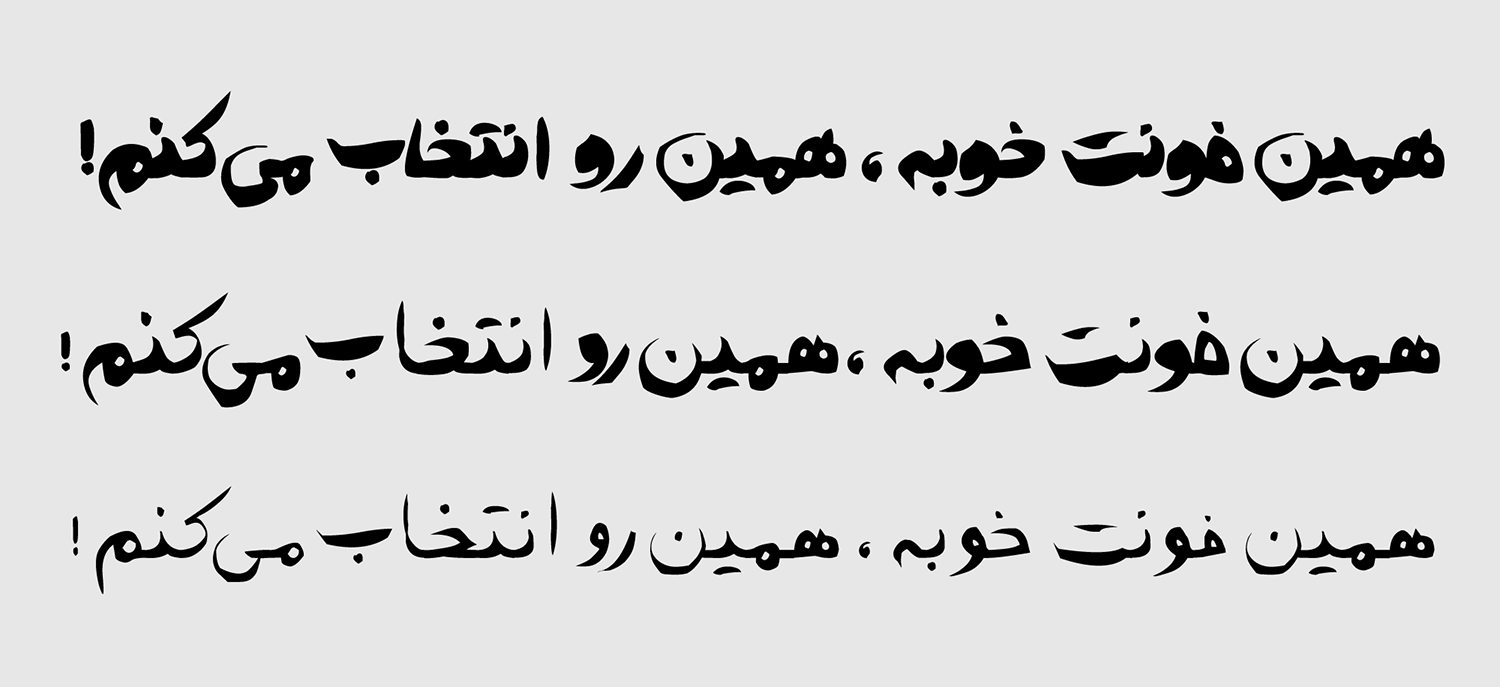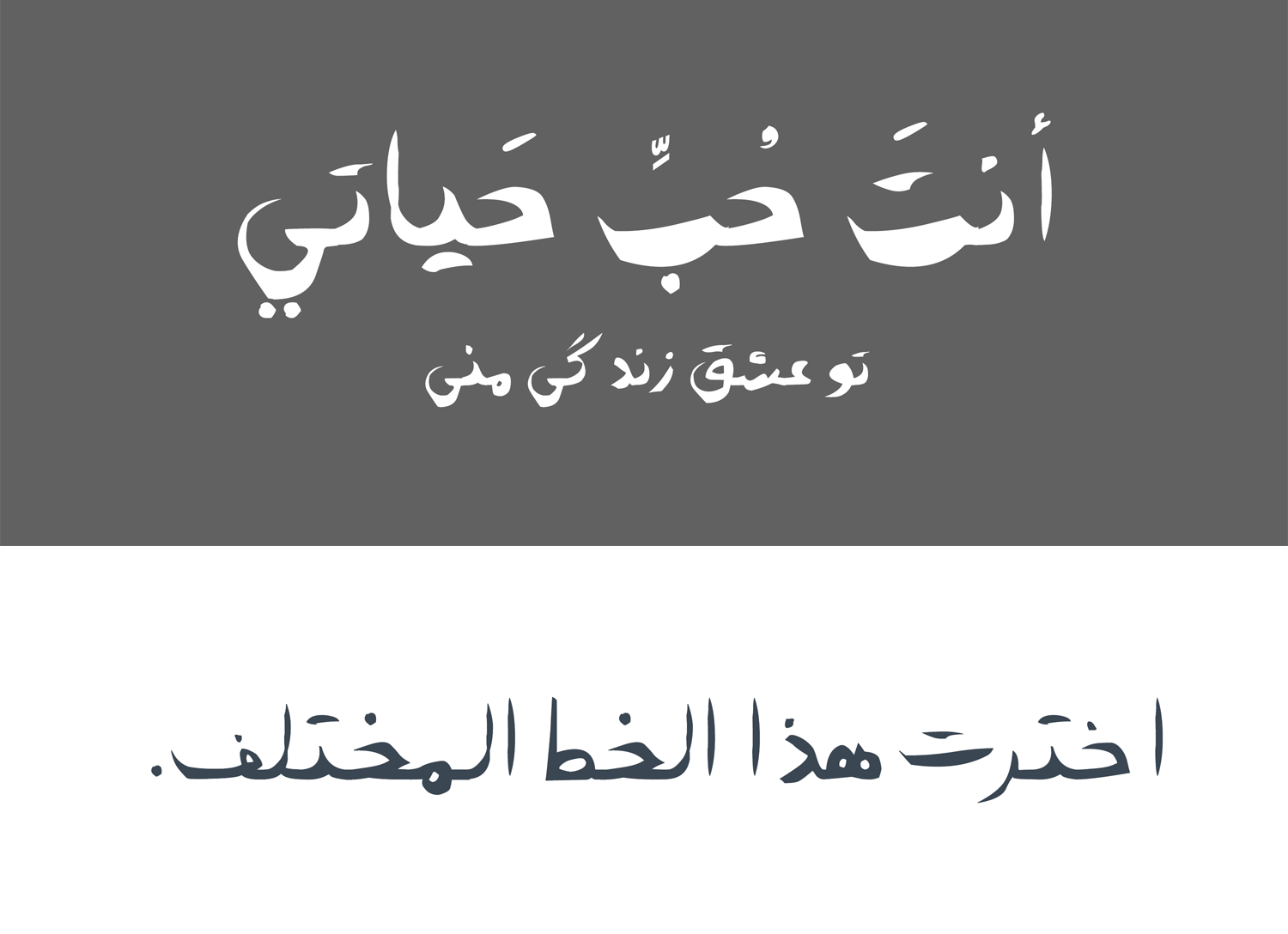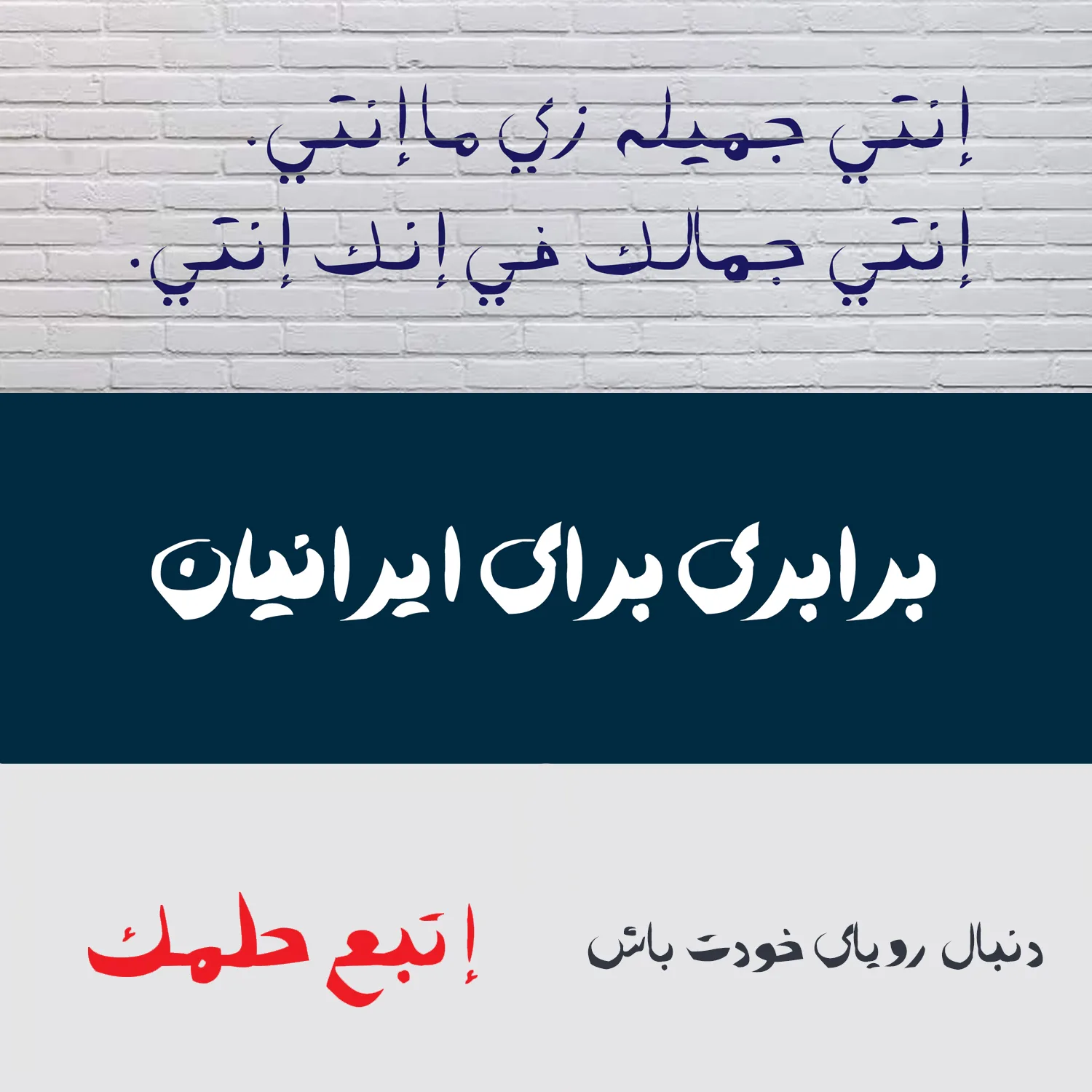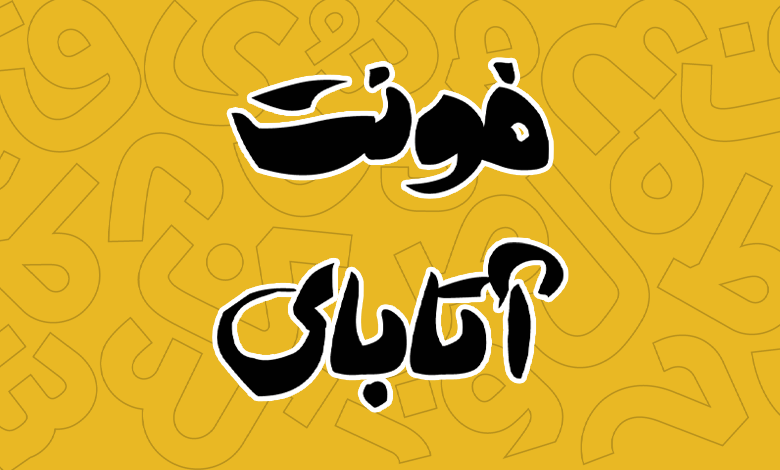
فونت آتابای (Atabay)
| طراح | هادی ارجمند |
فونت آتابای (Atabay) در دسته فونتهای فانتزی و نمایشی قرار دارد که توسط هادی ارجمند در قالب یک فونت شخصی برای انجام کارهای گرافیکی ساخته شده است که پس از مدتی برای استفاده عموم عرضه گردید.
این فونت دستنویس با الهام گرفتن از سبک قلم مو و جوهر طراحی شده است؛ که شامل حروف، نقاط، منحنیها، شکستگیها و ترکیبات نامنظم متنوعی است. با وجود بینظمیهای نمایشی، اما حروف دارای حرکات و ساختارهای فیالبداههای هستند که آن را از دیگر قلمهای دستنویس متمایز کرده است.
در ادامه این نوشته از سایت فونتچی به نقد و بررسی فونت آتابای خواهیم پرداخت که میتوانید از این قلم برای طراحی کارهای گرافیکی در حوزههایی که نیاز به سبک نوشتاری قلممو و جوهر نیاز دارید استفاده کرده و بدون نیاز به استفاده از طرحهای گرافیکی سخت و زمانبر در نرمافزارهای گرافیکی، به کمک فونت سریعا نیازهای خود را برآورده کنید.
معرفی و بررسی فونت آتابای (Atabay)
کاربرد اصلی فونت آتابای برای کارهای گرافیکی حوزه تبلیغات یا چاپ روی جلد کتابهاست. اما اصلیترین جایی که میتوان از این فونت استفاده کرد به همان دلیل طراحی آن برمیگردد.
همانطور که طراح فونت بیان داشته، این فونت بر اساس نیاز شخصی برای انجام کارهای گرافیکی با سبک قلم مو و جوهر ساخته شده است تا کار را برای ایجاد چنین سبک طرحهای گرافیکی سادهتر کند.
سبک و وزن فونت آتابای
فونت دست نویس آتابای از ۳ وزن معمولی، بولد و سیاه پشتیبانی میکند که نسخههای بولد و سیاه در شماره نسخه ۲.۰ به آن اضافه شدهاند.
ویژگی و مشخصات فونت Atabay
طراحی حروف در قلم آتابای بهصورت تکتک نگارش شدهاند و سپس در اجرای نرمافزاری اتصالها ایجاد میشود. طراح چندان پایبند به نظام دقیق پیوستگی مرسوم در فونتهای فارسی نیست و همه اینها با شخصیت غیرماشینی و فیالبداهه این قلم هماهنگ است.
در نتیجه با فونت نمایشی مواجه هستیم که جدا از زبان عربی، در زبان فارسی برای برخی ترکیبات یا در حالتی که از برخی اعراب و کاراکترهای کرسی بالا و پایین حروف استفاده شود، احتمالا دارای اختلالات یا ناهماهنگیهای جزئی باشد. اما در هر صورت این تایپفیس تقریبا تنها فونت ساخته شده بر مبنای قلممو و جوهر است.
پشتیبانی از زبان ترکی و عربی
فونت آتابای فارسی است و پشتیبانی کاملی از این زبان دارد. اما به لطف رسم خط عربی که ساختاری یکسان با نوشتار زبان فارسی دارد امکان استفاده از این فونت را در زبان عربی نیز خواهید داشت.
بر اساس ادعای طراح، با اینکه تمامی اعرابها در تنظیمات فونت برای این رسم خط پیاده سازی شده؛ اما برای زبان عربی ممکن است در برخی ترکیبات کلمات اعراب بهدرستی در جای خود ننشینند.
فونت آتابای برای استفاده در زبان ترکی و آذری که از رسم خط فارسی استفاده کنید نیز قابل پشتیبانی است و میتوانید از اعراب اختصاص داده شده برای زبان فارسی و عربی نیز برای این زبانها بهره ببرید.
از سوی دیگر پشتیبانی این فونت بر مبنای اعداد فارسی است و خبری از حروف و اعداد انگلیسی در این فونت نیست. در صورت تایپ حروف و اعداد انگلیسی از فونت دیگری بسته به تنظیمات Type سیستم عامل یا نرمافزار شما استفاده خواهد شد.
سبک نقاط نامنظم
سبک نقطه گذاری در فونت آتابای متفاوت است و همه نقاط از طراحی چسبیده به هم پشتیبانی میکنند. همانطور که در فونت آوینی مشاهده کردیم، در فونت دست نویس آتابای هم از همان سبک نقطه گذاری استفاده شده است.
نقاط این فونت در حالت نقطه تکی دارای ظاهری نسبتا گرد با تغییرات جزئی هستند که پیکسلهایی از فونت بیرون زده شده تا همان حس تایپ با قلممو را داشته باشد.
اما در مورد نقاط دو و سهتایی وضعیت کمی متفاوت است:
- نقاط دوتایی در حرف «تـ» با ساختار ذکر شده که در ابتدای کلمات است، در مقایسه با ترکیب «ـت» در انتهای کلمات متفاوت از یکدیگر هستند. در حالت اول نقطههای بههم چسبیده فشرده و خط انتهایی که گویی قلممو از روی صفحه برداشته شده فشردهتر است؛ در حالتی که در سبک «ت» انتهایی، کشیدهتر و خط انتهایی قلم کشیده شده از روی صفحه نیز طویلتر است.
- در خصوص نقاط سهتایی هم اینطور است که برای حروف «ث، ژ، ش» که نقاط در بالا هستند، سبک نقطهگذاری در مقایسه با حروف «پ، چ» معکوس شده است.
- یک تفاوت دیگر هم در نقاط دوتایی و سهتایی مربوط به نقطه شروع و پایان نقاط است. در نقاط دوتایی نقاط از سمت چپ آغاز شده و در سمت راست به پایان میرسند در حالی که در نقاط سهتایی این روند برعکس است.
نکته پایانی که باید در خصوص فونت آتابای به آن اشاره کرد، وقتی از صفحه کلید انگلیسی استفاده میکنید، کاراکترهای خاص و سمبلها همچون کاما، علامت تعجب و… که در همه زبانها مشترک هستند از گلیف فارسی تبعیت کرده و با فونت آتابای تایپ خواهند شد. در حالی که حروف انگلیسی در این فونت کار نشده و فاقد گلیف هستند که در این حالت با فونت پیشفرض سیستم عامل تایپ خواهند شد.